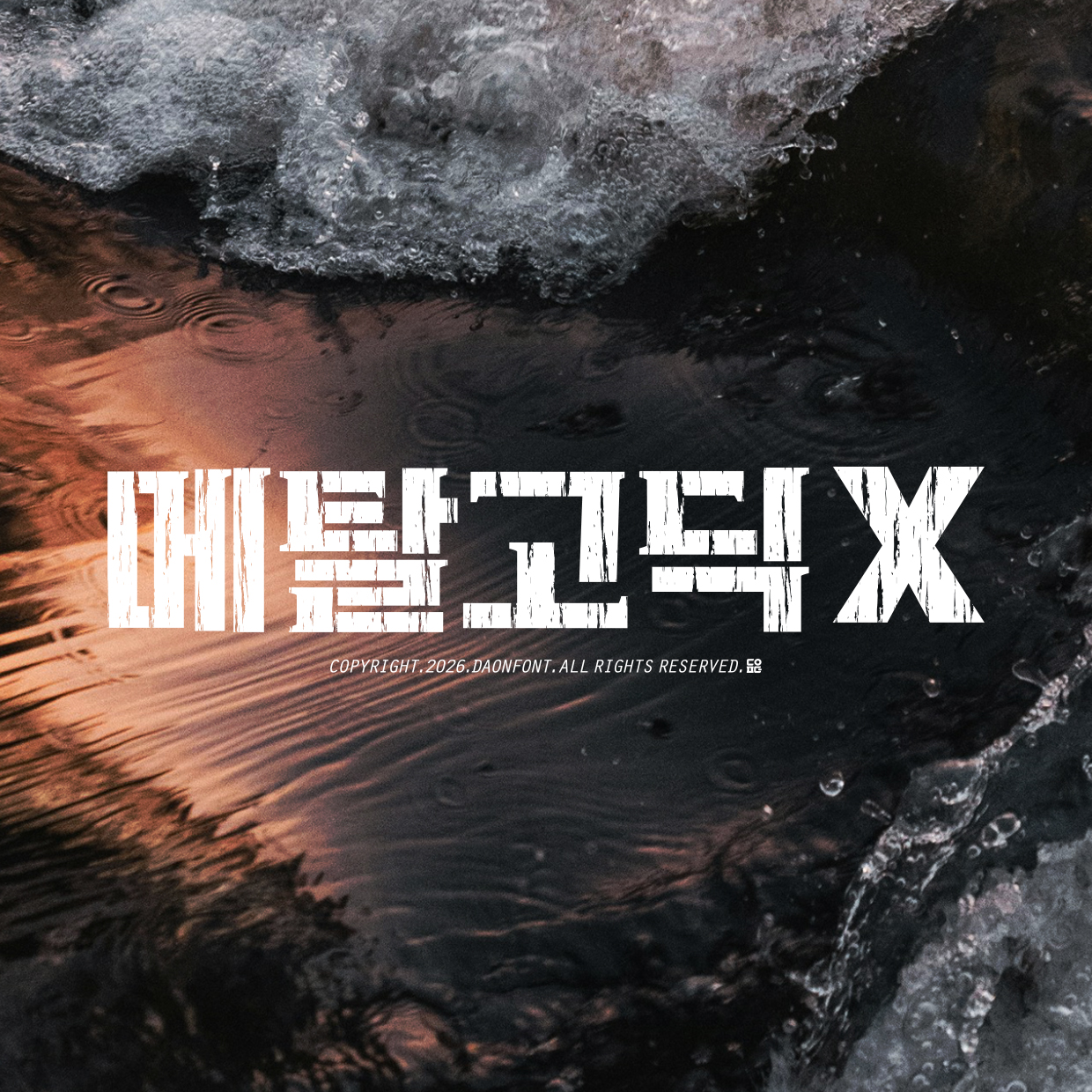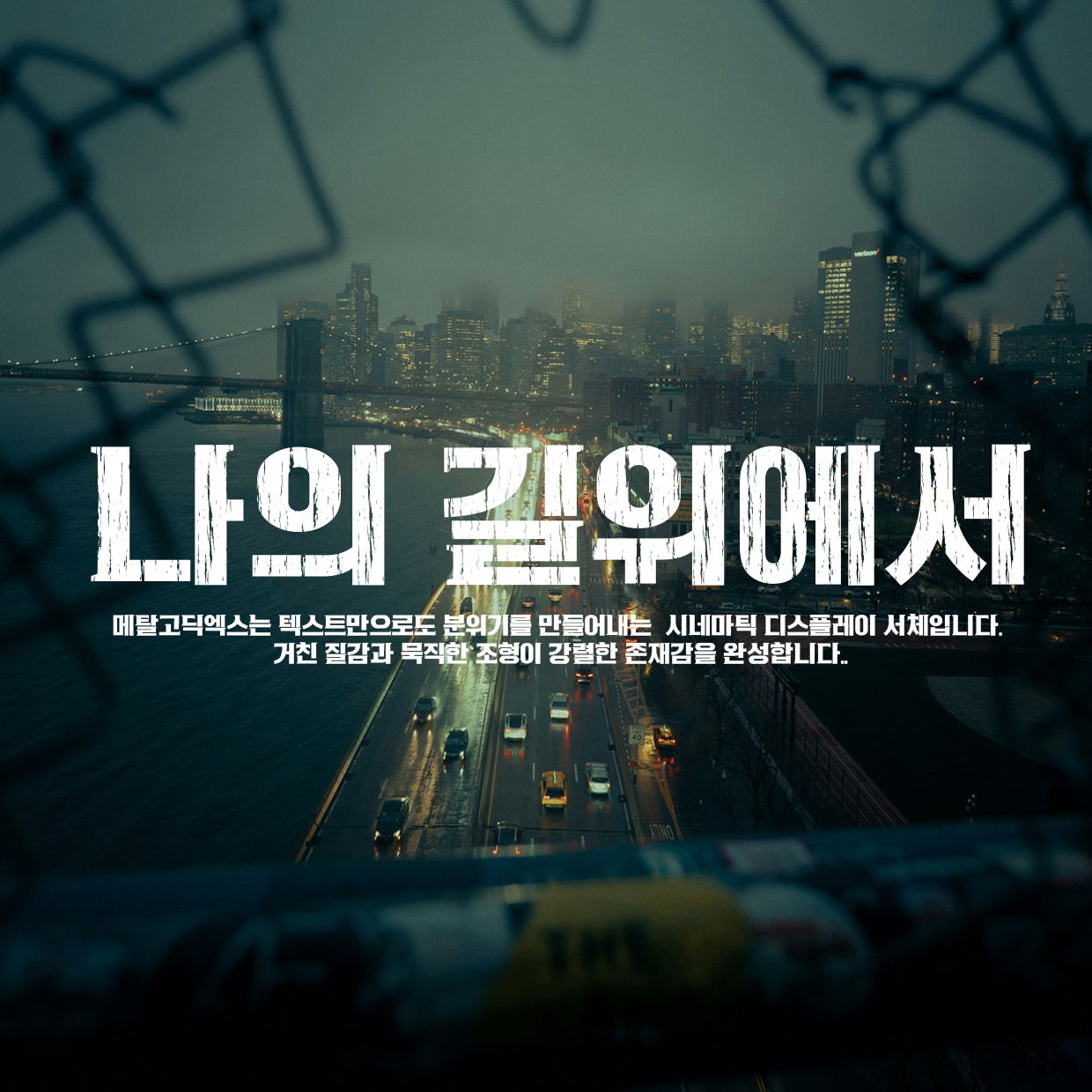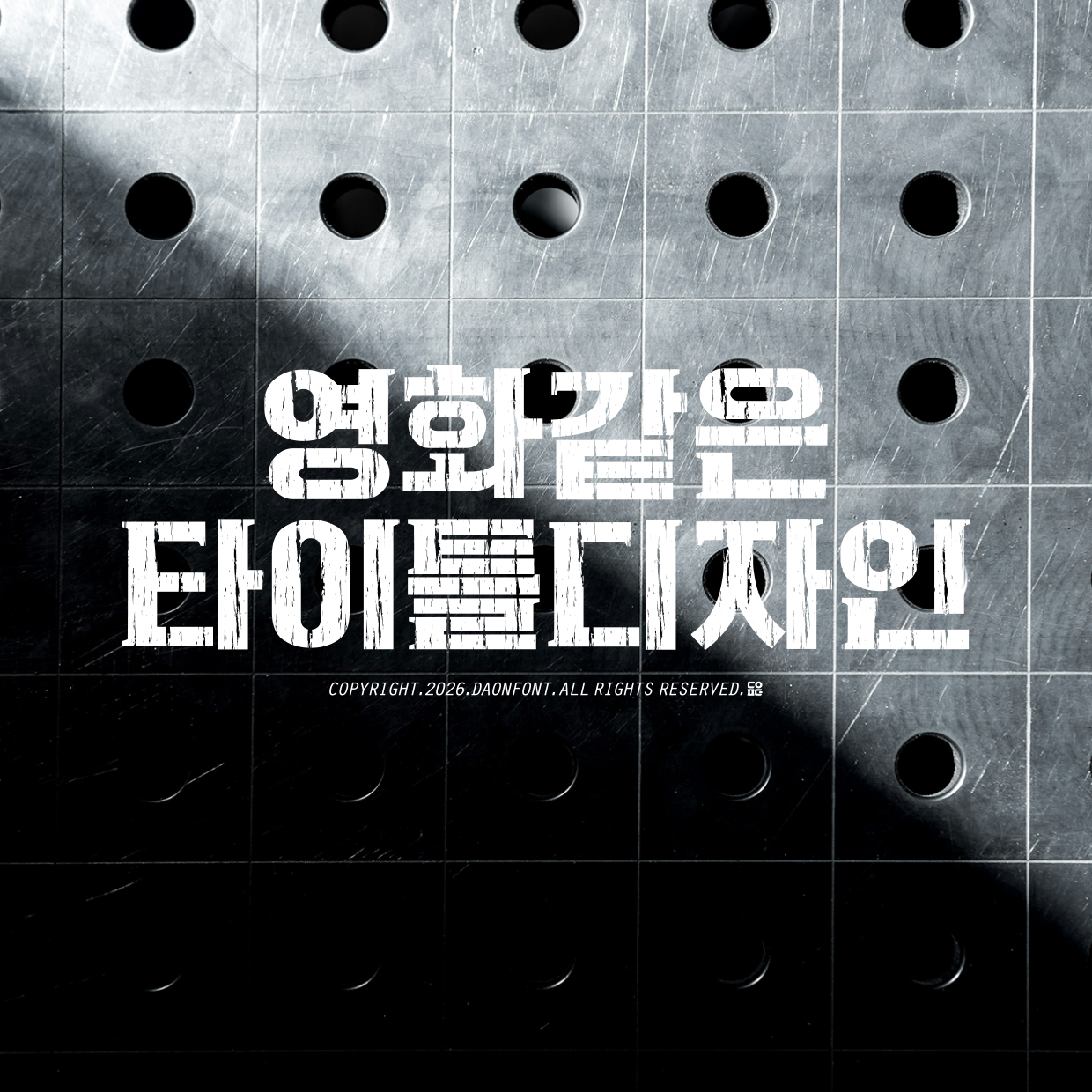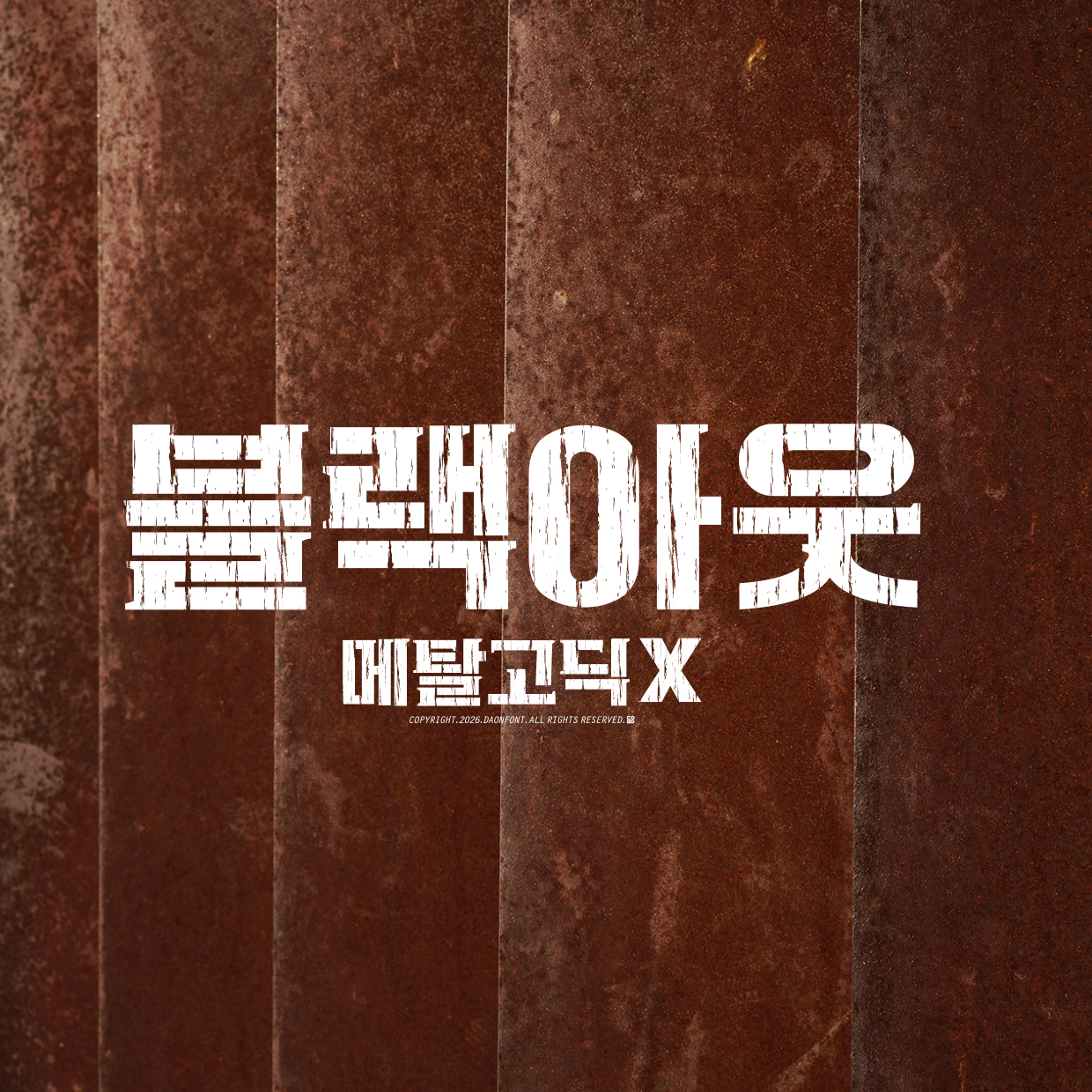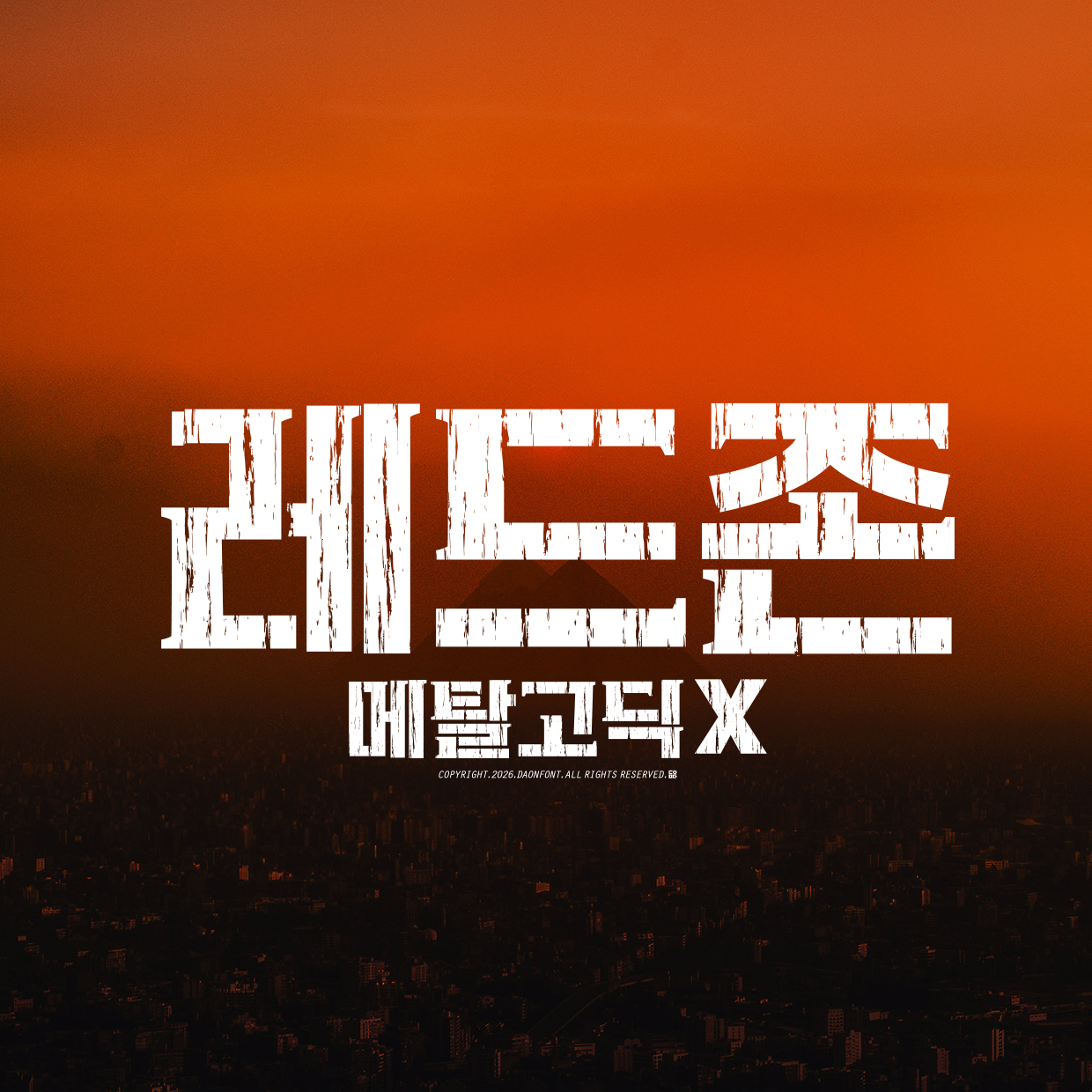
다온폰트 신서체 "메탈고딕X" 6월 출시 예정
메탈고딕에 이어, 새로운 디스플레이 서체 메탈고딕X를 소개합니다.
메탈고딕X는 텍스트만으로도 강렬한 분위기를 연출할 수 있도록 설계된 시네마틱 디스플레이 서체입니다.
거친 질감과 묵직한 조형미를 바탕으로 강한 인상과 존재감을 표현하며,
메탈고딕의 강인한 감성을 더욱 확장하여, 보다 극적이고 인상적인 비주얼 경험을 제공합니다.